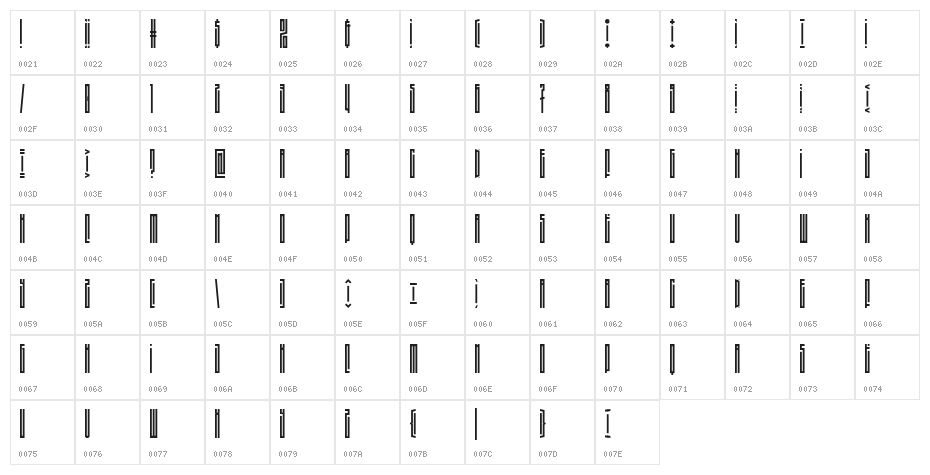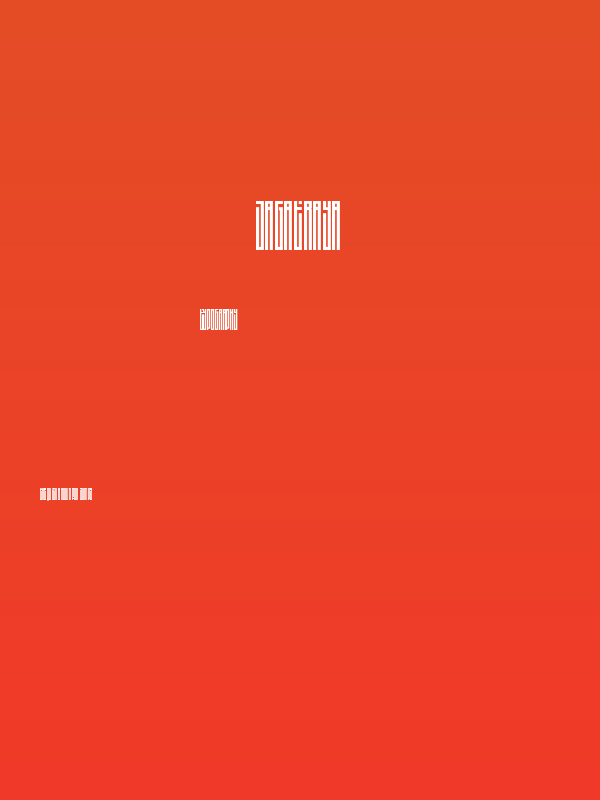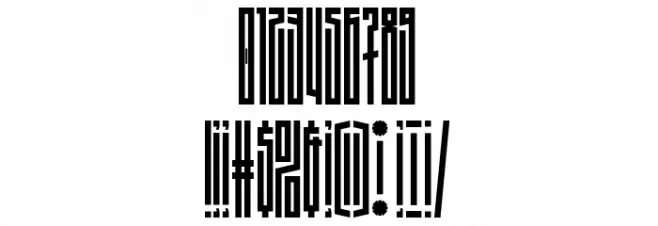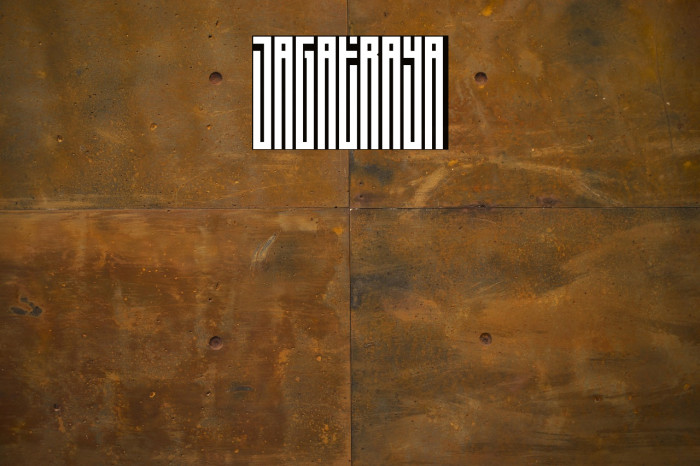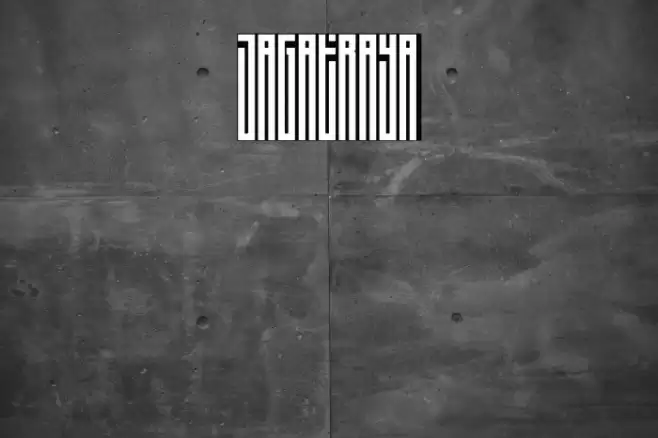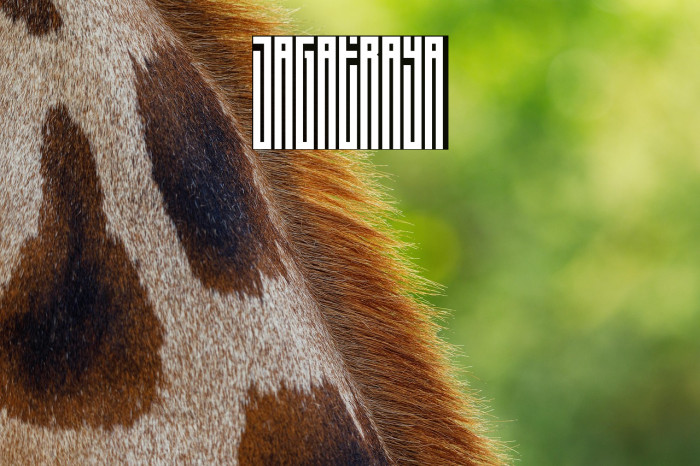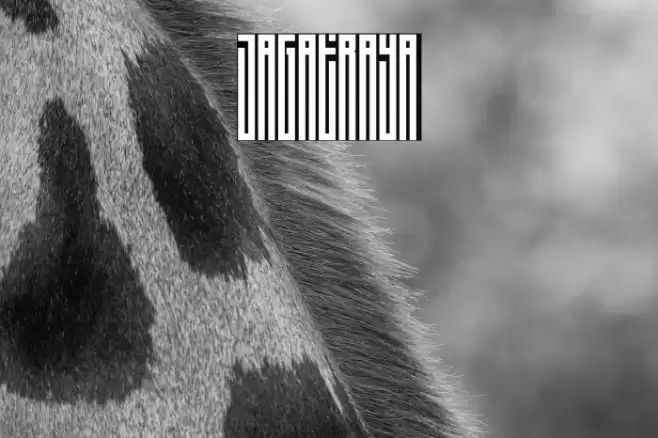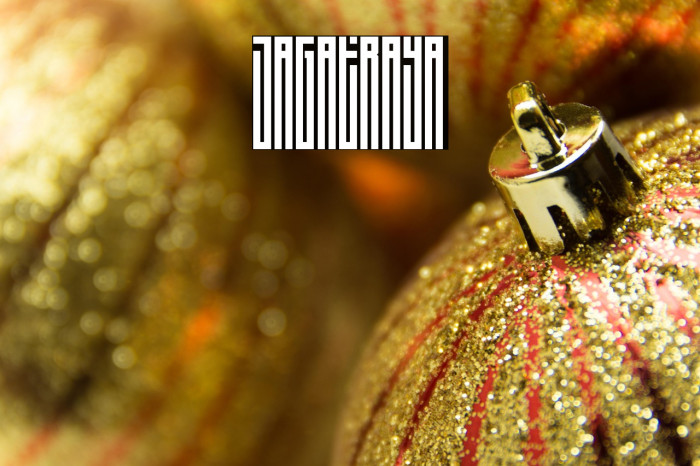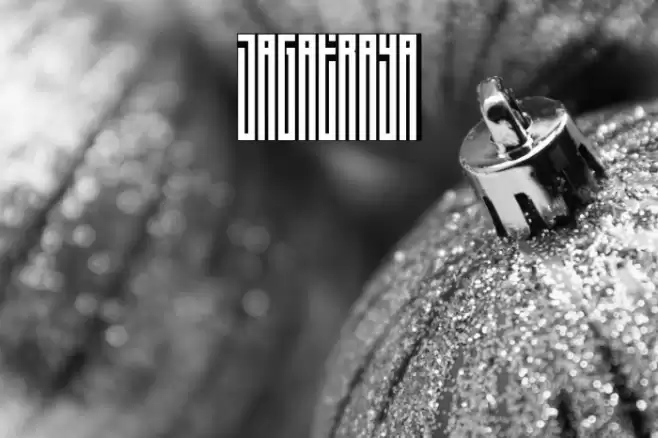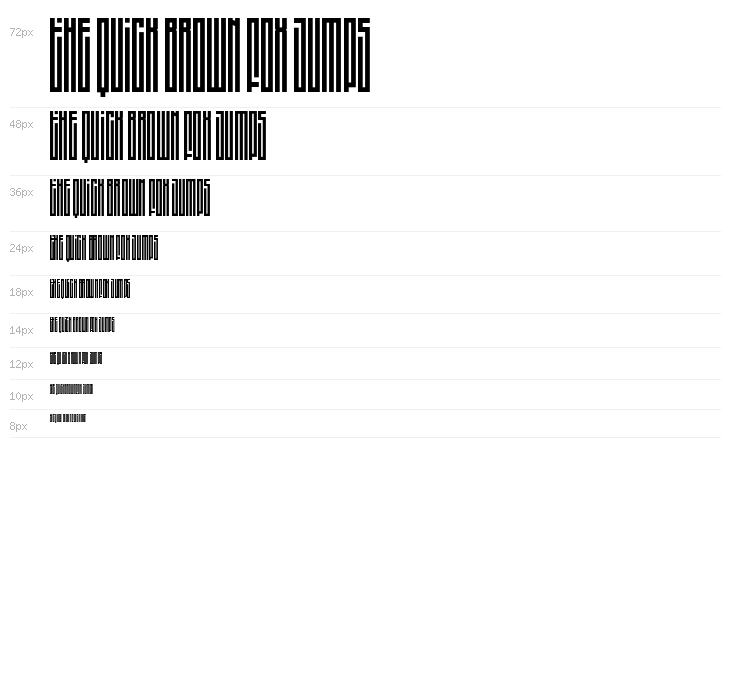
JAGATRAYA Font
✎ Art Deco
| Categorii | Art Deco |
| Stil general | Modern, Art Deco |
| Proiecte propuse | Ideal for posters, album covers, branding materials, and any project needing a bold, artistic statement. |